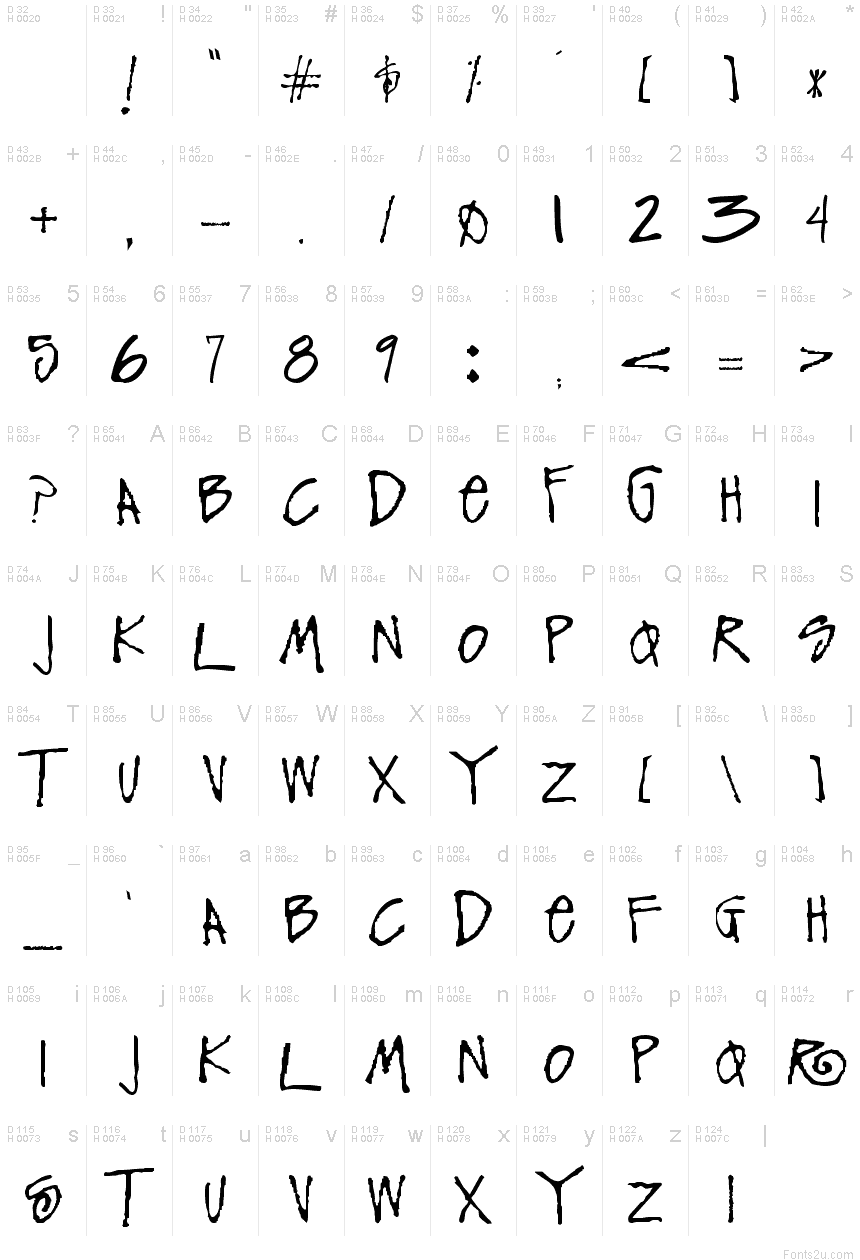
Funky to darmowy, odręczny krój pisma o wysokich, cienkich liniach, które wyglądają, jakby zostały wydrapane na ścianie kapcającym markerem. Litery chwieją się i pękają, nadając każdemu słowu niespokojny, nieszablonowy rytm – coś pomiędzy horrorem a undergroundowym plakatem koncertowym. Surowa, ziarnista tekstura przyciąga wzrok i nie pozwala zignorować swojej obecności.
Używając Funky, wniesiesz chaos i charakter do plakatów koncertowych, okładek płyt indie, grafik na Halloween, fanzinów, brandingu skate lub streetwearu oraz odważnych materiałów do social mediów. Ten darmowy font najlepiej sprawdza się w dużym rozmiarze, gdzie jego poszarpane krawędzie i wyciągnięte formy mogą w pełni wybrzmieć. W przypadku drobniejszego tekstu zestaw go z czystym, geometrycznym krojem bezszeryfowym, aby zachować czytelność, podczas gdy nagłówki Funky będą wykrzykiwać treść.